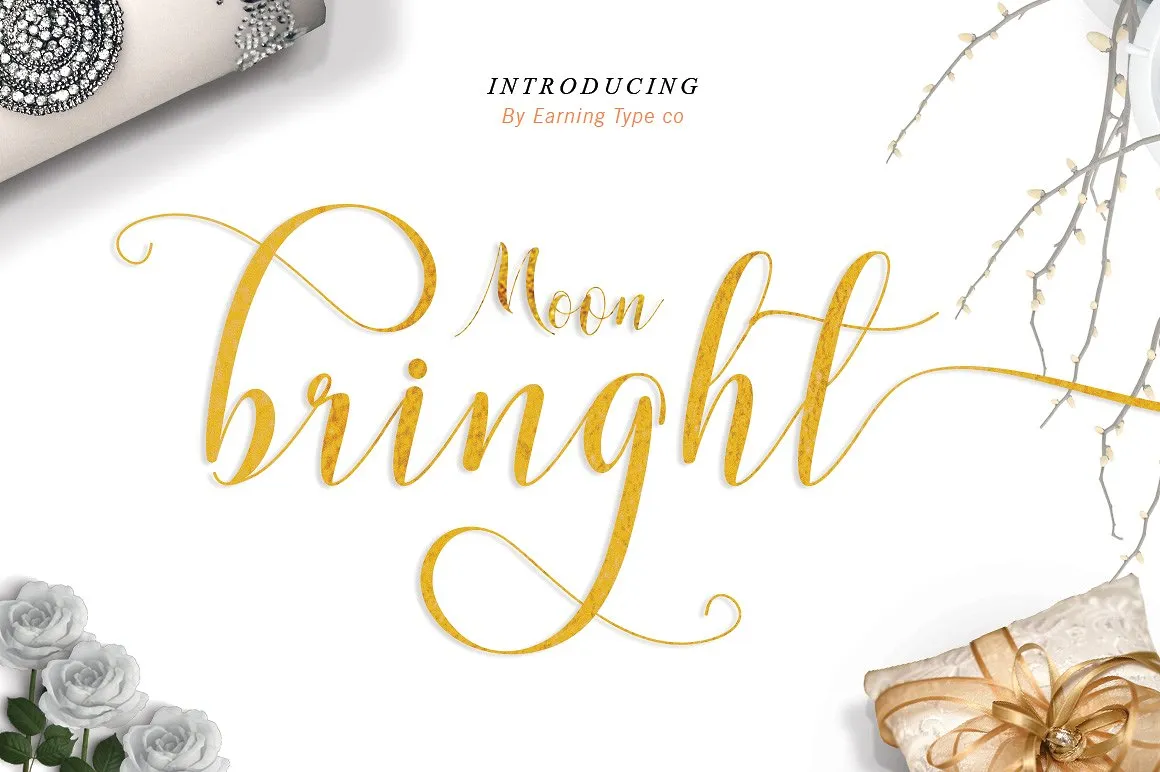
A Moonbringht Script Font é uma deliciosa mistura fresca e moderna do script, com influências góticas e leves toques decorativos que criam um estilo único e autêntico. Essa fonte tem 496+ caracteres, incluindo alternativas de letras maiúsculas e minúsculas e mais swashes para garantir um visual brilhante e chamativo. Ideal tanto para cartas de cumprimento quanto para materiais de marca ou selos empresariais, a Moonbringht Script é perfeita para dar vida à sua próxima criação de design. Seja ela um convite especial, uma etiqueta de produto, uma ilustração para um post ou até mesmo uma instalação em uma parede, essa fonte trará seu trabalho ao próximo nível. Não deixe de baixar e experimentar a Moonbringht Script para adicioná-lo à sua coleção de recursos gráficos.